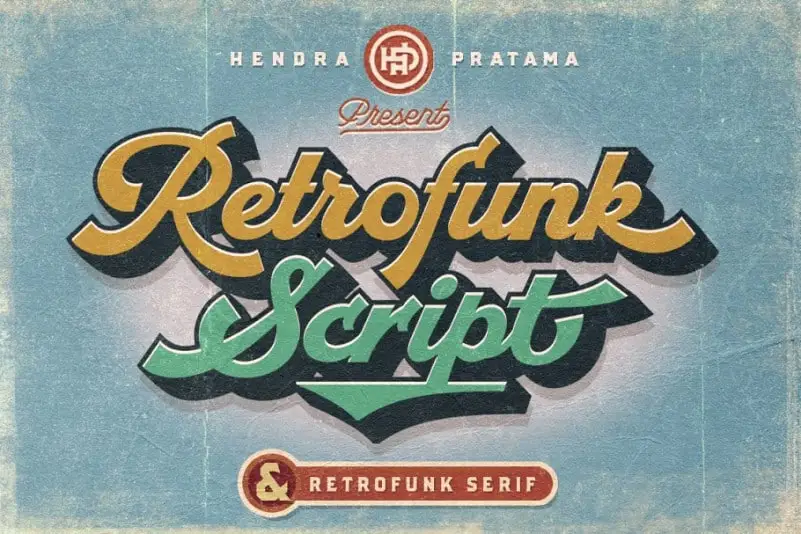
A Retrofunk Font Duo é uma combinação única de estilo Script e Serif que oferece a você uma fonte ideal para criar riffs memoráveis e criativos. Este conjunto exclusivo, projetado por Hendra Pratama, inclui não apenas o Script como também o Serif font. A combinação de ambos sempre cria um resultado impactante em logotipos, signboard e até mesmo marcas simples. O que torna a Retrofunk Font Duo ainda mais impressionante é seu vasto número de alternativas com Unicode PUA incorporadas. Estas alternativas adicionais permitem criar uma tipografia imponente, poderosa e variada para Flyers, Adesivos de painel, capas de livros, títulos ou qualquer outro tipo de fonte vintage ou retrô. Essa fonte é perfeita para quem quer dar um toque de personalidade ao design de seu produto sem comprometer a legibilidade. Ela é o alvo perfeito para designers que desejam incorporar elementos retro na sua identidade visual, seja em logotipos de marcas ou em materiais promocionais. Seja você um designer gráfico experiente ou iniciante, certamente encontrará nesta fonte Duo uma ferramenta versátil e funcional para alcançar seus objetivos criativos. A Retrofunk Font Duo é uma excelente escolha tanto para o desenvolvimento de logotipos como para materiais publicitários, oferecendo aos designers o poder de criar design gráfico original e atemporal.